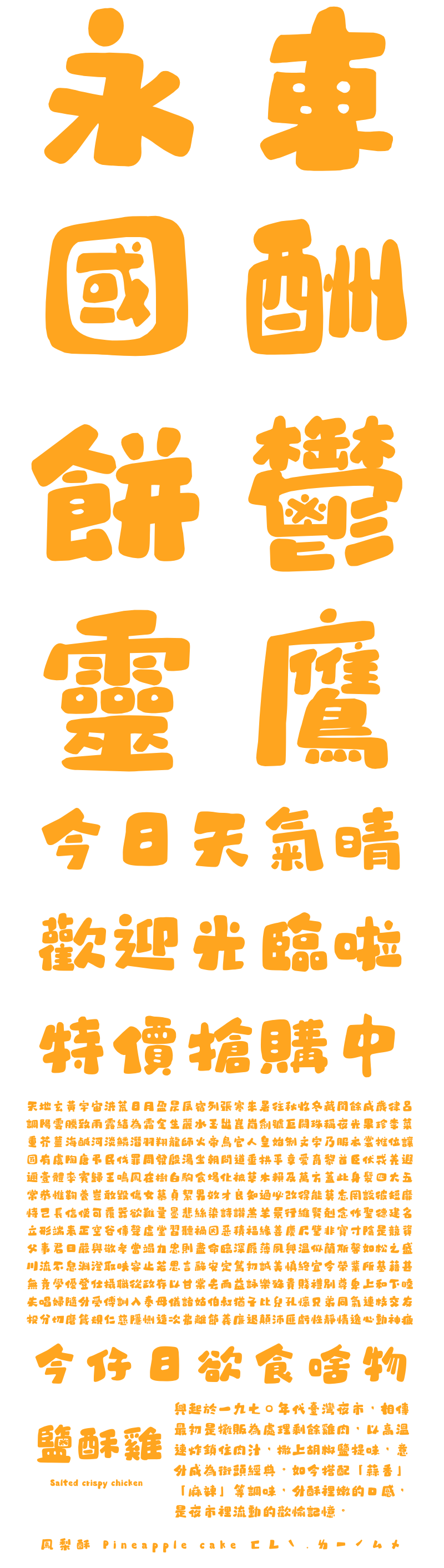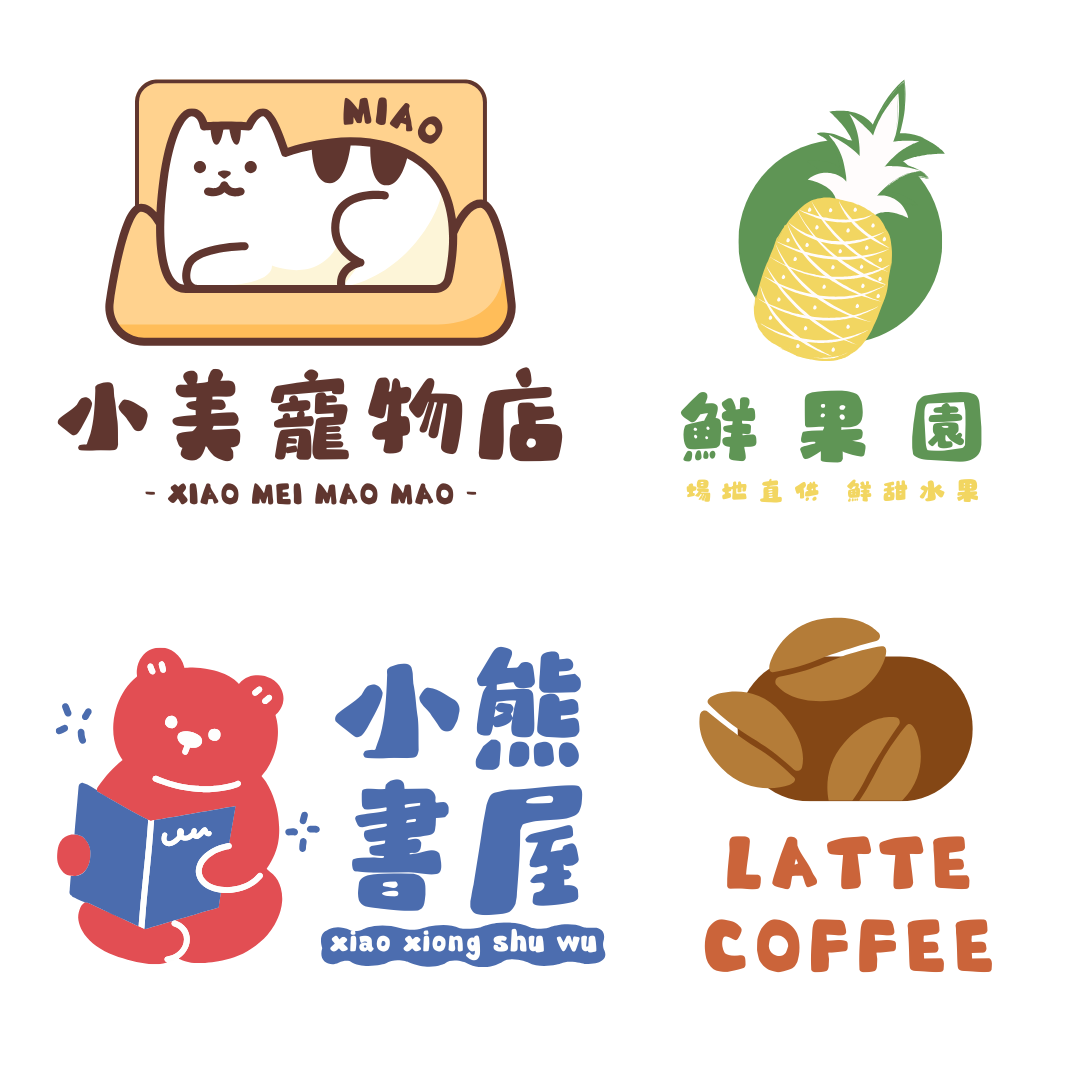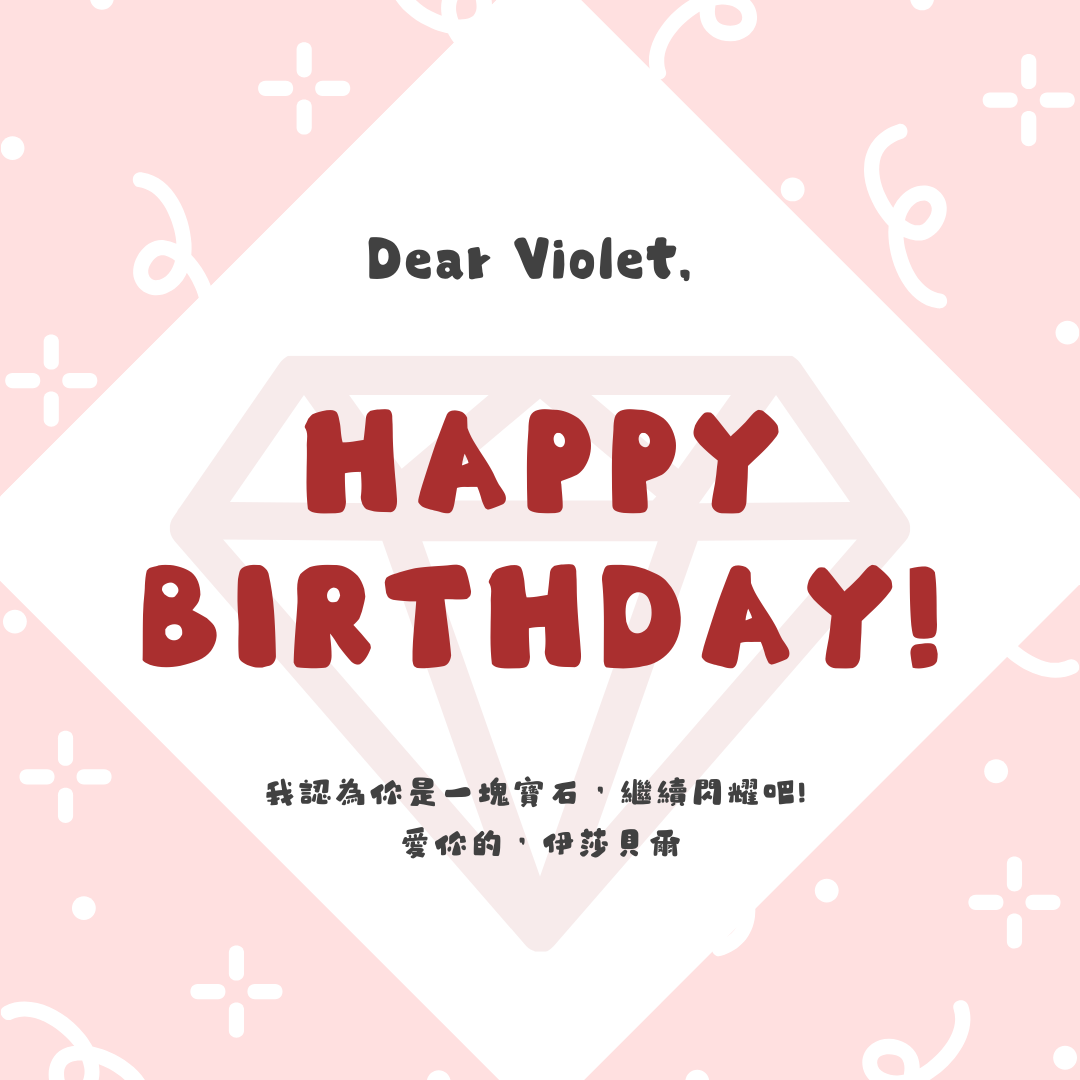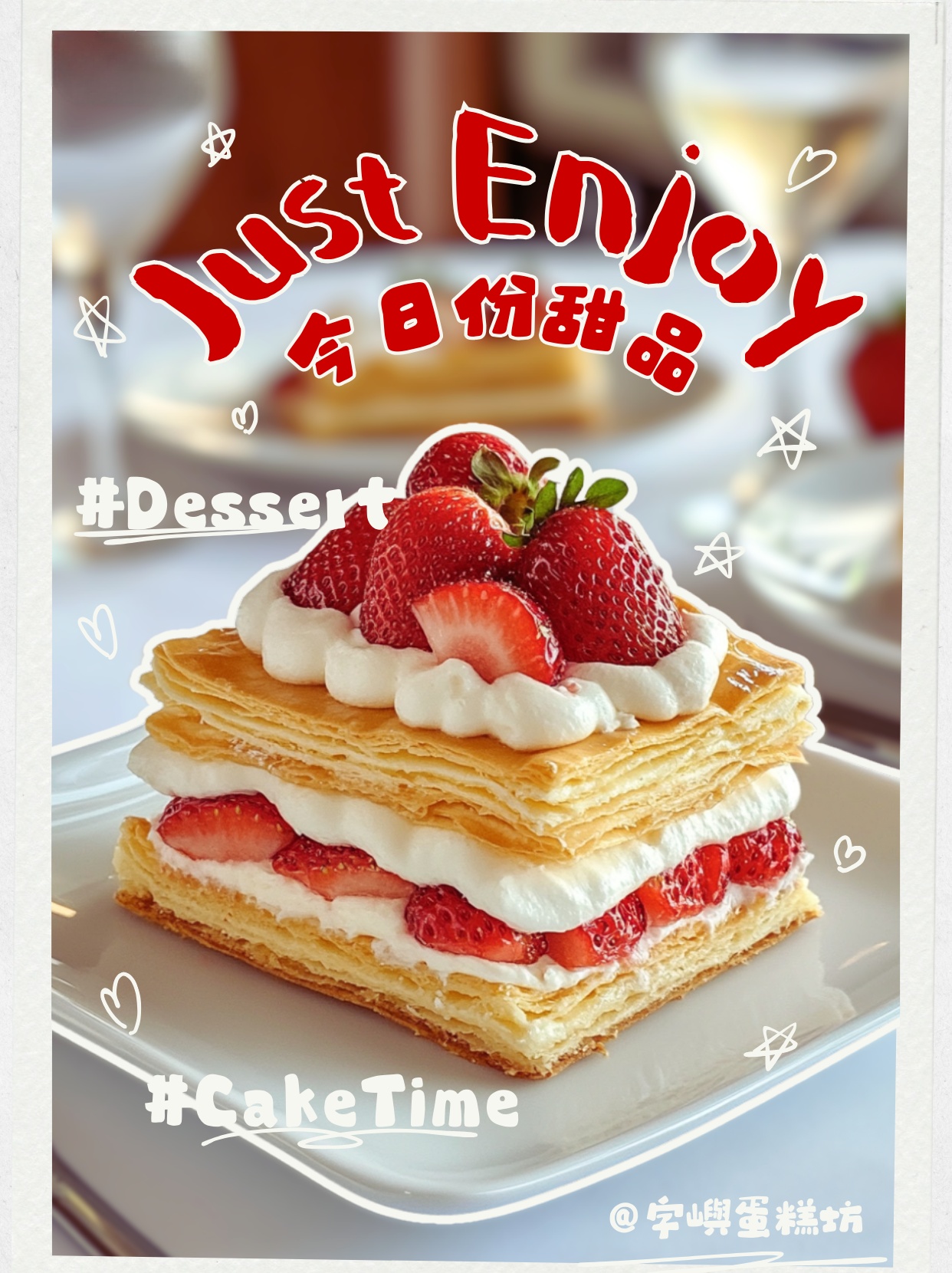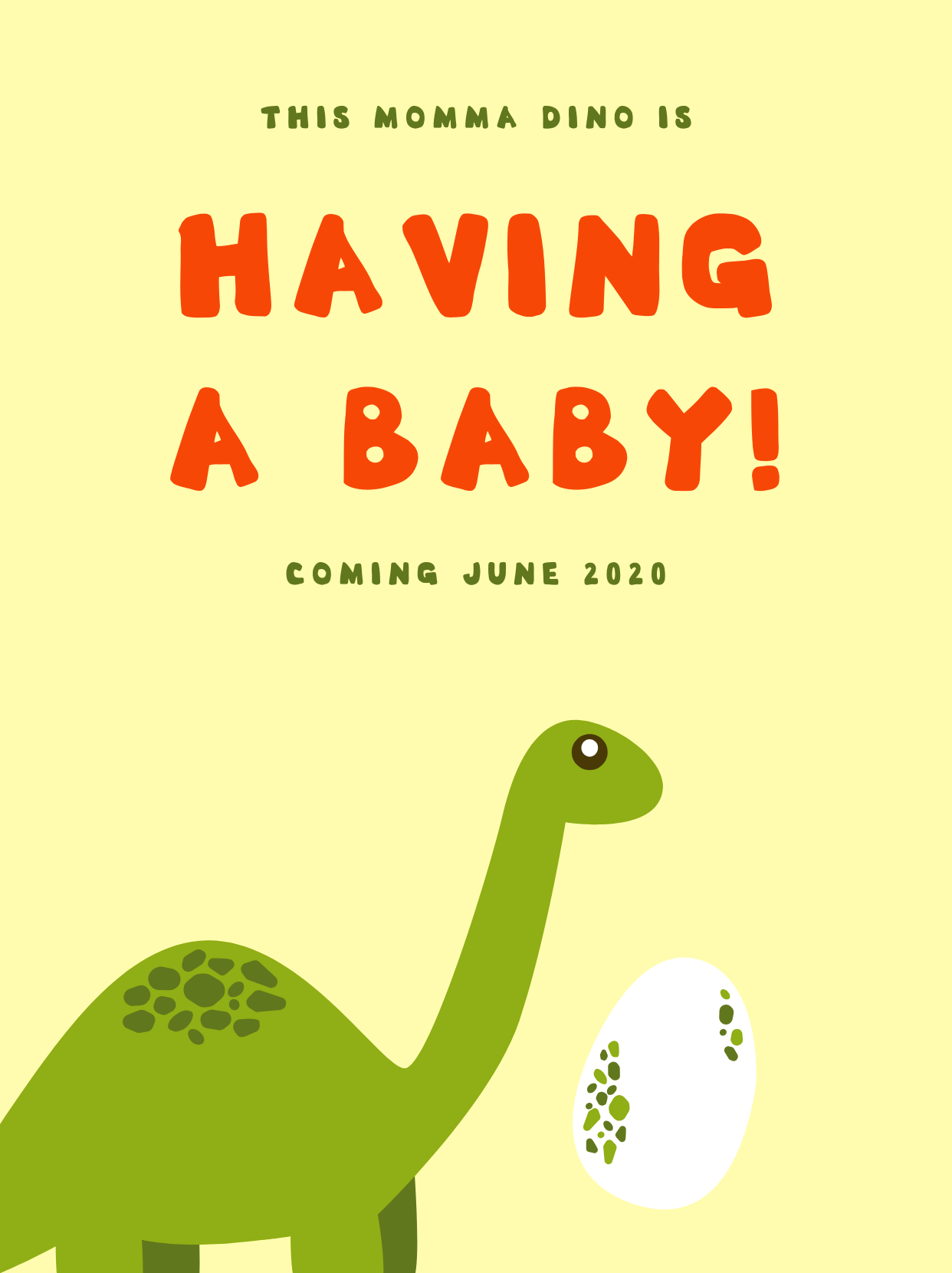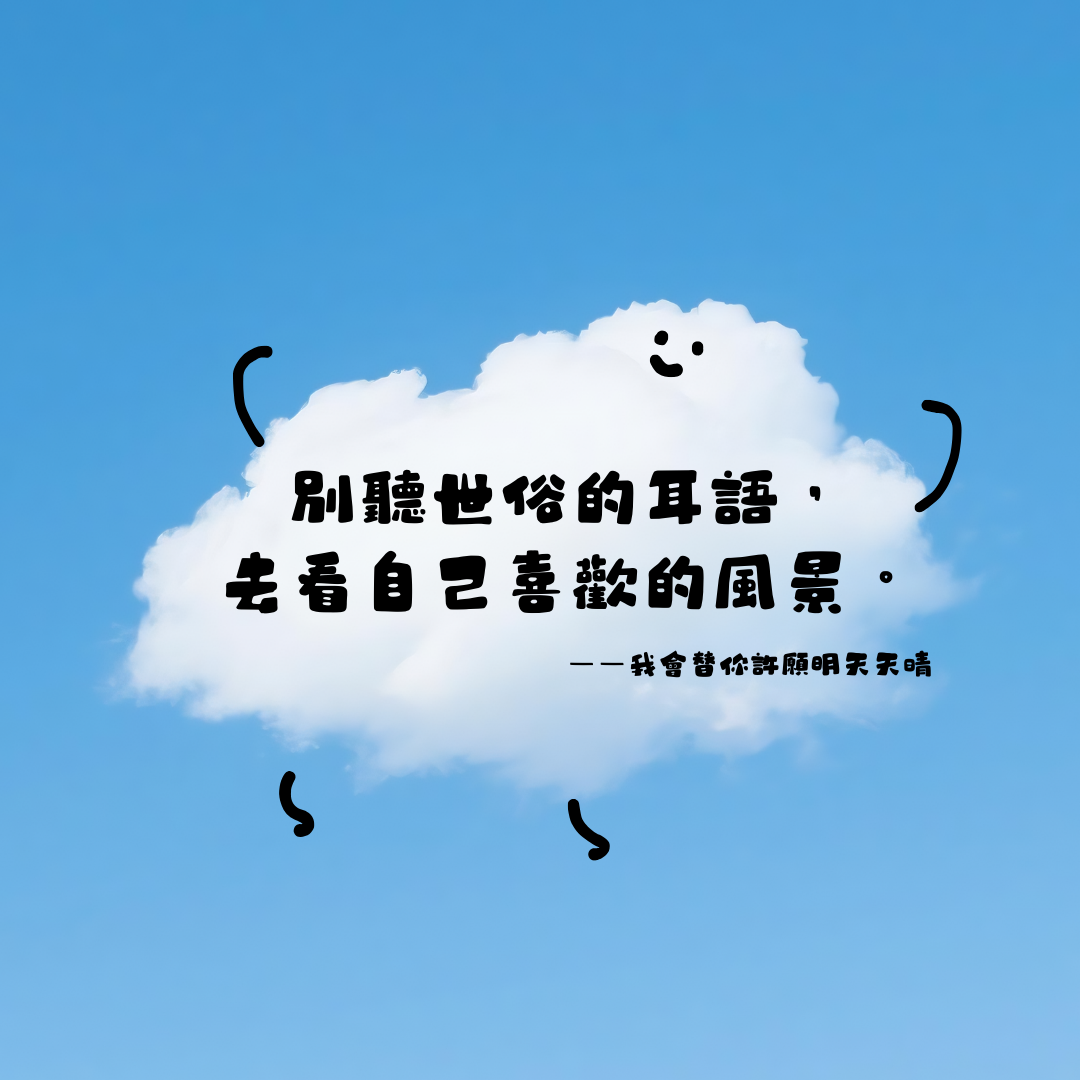
字嶼泡芙體TC
想像一下,剛出爐的法式泡芙——外殼輕盈酥脆,內餡飽滿蓬鬆,咬下的瞬間,空氣感與甜蜜在口中化開,那是直達心底的純粹幸福。
現在,這份讓人忍不住微笑的「蓬蓬魅力」,被精心烘焙成文字了!讓每個字都像裹上鮮奶油的泡芙,圓潤、膨鬆的可愛字型。
不是單純的放大加粗!在經過設計師的精心調整後,文字整體視覺飽滿卻不顯笨拙,每個筆畫都像被溫柔地吹入了空氣,形成具有空氣感的微膨弧度。
我們希望這款字有無限的可能性:
- 甜點/咖啡/餐飲品牌: 菜單上的品項名稱、吸睛的促銷海報、精緻的包裝貼紙、IG限動的誘人訊息...
- 親子樂園: 兒童繪本標題、玩具包裝上的說明、幼兒園可愛通知單、遊樂園歡樂海報...
- 傳遞心意: 生日賀卡上的祝福、派對邀請函的熱情、情人節的甜蜜絮語、年節賀卡的喜慶...
- 社群互動: Facebook 可愛公告、Instagram 限動的重點標註、LINE 貼圖的生動文案、KOL 的親切分享文...
- 文創設計: 手帳裡的可愛標題、療癒小語貼紙、文青品牌標語、溫柔系書籍封面...
字嶼泡芙體 TC:甜美俏皮的字體新寵
字嶼泡芙體 TC 風格鮮明,初見便能牢牢抓住眼球。它的設計靈感彷彿源自那令人垂涎欲滴的泡芙美食,將泡芙的特質巧妙融入字體筆畫之中。筆畫圓潤飽滿,恰似泡芙那鼓鼓囊囊、充滿空氣感的外皮,給人以柔軟、蓬鬆的視覺感受,傳遞出甜美與溫馨。
從字形結構來看,字嶼泡芙體 TC 並不追求傳統字體的規整刻板,而是呈現出一種自然隨意的狀態。部分字形略微傾斜,像是俏皮的孩童在紙上歪歪扭扭書寫,充滿了天真爛漫的氣息,為字體賦予了獨特的動態感,彷彿這些字隨時都會在頁面上跳躍起來。而且,字與字之間的間距經過精心調整,疏密得當,既保證了良好的可讀性,又讓整個排版看起來錯落有致,富有韻律美,如同擺放整齊又各具姿態的泡芙甜點,給人帶來視覺上的享受。
適用場景:多領域的甜美擔當
- 兒童文創產品設計
- 無論是兒童故事書的標題設計,用它書寫「小兔子的奇幻冒險」,圓潤俏皮的字體瞬間將孩子們帶入充滿童趣的幻想世界,激發孩子們對閱讀的興趣;還是兒童文具,如彩色鉛筆的包裝、筆記本的封面,使用該字體標註品牌或書寫溫馨話語,都能憑藉其甜美可愛的風格,深受孩子們的喜愛。在幼兒園的裝飾牆、活動海報設計中,字嶼泡芙體 TC 也能大顯身手,營造出活潑、歡快的校園氛圍,助力孩子們在充滿趣味的環境中快樂成長。
- 甜點烘焙宣傳物料
- 對於甜點店、烘焙坊而言,字嶼泡芙體 TC 是宣傳的得力助手。在店鋪招牌上,用這款字體書寫店名,如「甜美泡芙坊」,遠遠望去,便能吸引路人的目光,傳遞出店鋪的甜美定位。店內的菜單設計,使用字嶼泡芙體 TC 展示「草莓奶油泡芙」「巧克力爆漿泡芙」等甜點名稱,字體與甜點相得益彰,勾起顧客的食慾。宣傳海報上,以字嶼泡芙體 TC 搭配精美的甜點圖片,宣傳新品上市或促銷活動,能有效吸引顧客進店消費,提升店鋪的知名度和銷售額,讓每一位顧客都能感受到甜點帶來的甜美誘惑。
- 少女心主題活動策劃
- 在以少女心為主題的活動策劃中,字嶼泡芙體 TC 是營造氛圍的關鍵元素。無論是情人節的浪漫約會活動、女生節的慶祝派對,還是少女主題的生日聚會,從活動邀請函上的「浪漫之約,期待與你相遇」,到現場裝飾的標語「綻放少女心,暢享美好時光」,字嶼泡芙體 TC 都能將活動的浪漫、溫馨氛圍烘托得淋漓盡致。它柔和的線條和俏皮的風格,與少女心主題完美契合,讓每一位參與者都沉浸在甜美美好的氛圍中,為活動增添獨特魅力,留下難忘回憶。
- 社群媒體創意內容
- 在社群媒體平台上,為了吸引用戶的關注,創意內容的呈現至關重要,字嶼泡芙體 TC 在此領域也能發揮重要作用。在美食博主分享甜點製作教程的圖文內容中,使用該字體標註步驟、介紹食材,能讓整個教程看起來更加生動有趣;時尚美妝博主發布的少女風穿搭分享中,用它來撰寫標題和描述,如「甜酷少女風穿搭秘籍」,能更好地吸引目標受眾的目光,增強內容的吸引力和傳播力。字嶼泡芙體 TC 為社群媒體上的創意內容增添了一抹獨特的色彩,幫助博主們在眾多資訊中脫穎而出,收穫更多的點讚與關注。
字元與編碼:豐富全面,便捷應用
字嶼泡芙體 TC 擁有豐富的字元庫,以台語常用標准漢字為標准,參考jf7000字集,包括注音符號、歐文字符、阿拉伯數字和標點符號,總字符約7640字以上。涵蓋了日常生活和設計中常用的漢字、字母、數字以及各類標點符號,總計數量可觀的字元碼位。
無論是面向大眾的設計作品,還是涉及到國際交流、英文元素的設計專案,字嶼泡芙體 TC 字體都能提供字元支持。(目前字元集先以台語常用標準字為基礎建置,後續會逐步規劃擴充在地化用字,期待未來能更完整地服務臺語書寫需求。)在處理英文單詞或數字信息時,其字母和數字的設計與漢字相互呼應,保證了整體排版的和諧統一。豐富的字元資源讓設計師在創作過程中可以更加專注於發揮創意,靈活地運用這款字體打造出各種獨具匠心的設計作品。
字嶼泡芙體 TC 以其甜美俏皮的獨特風格、廣泛的適用場景、豐富全面的字元資源以及嚴格的版權保護,在字體設計領域嶄露頭角。它如同泡芙帶來的甜美味覺體驗一般,用獨特的魅力為各類設計作品注入活力,幫助設計師們將創意完美呈現。無論您是專業的設計師,還是有設計需求的企業或個人,字嶼泡芙體 TC 都可能是您在追求甜美、俏皮風格設計時的理想之選,讓您的作品在眾多資訊中脫穎而出,吸引更多目光,傳遞出滿滿的甜美與溫馨。
字嶼泡芙體TC
已涵蓋7519個臺灣常用漢字。
支援字型:常用國字標准甲表,及部分次常用國字標準乙表
含字符集:繁體字符 字母 標點符號 數字